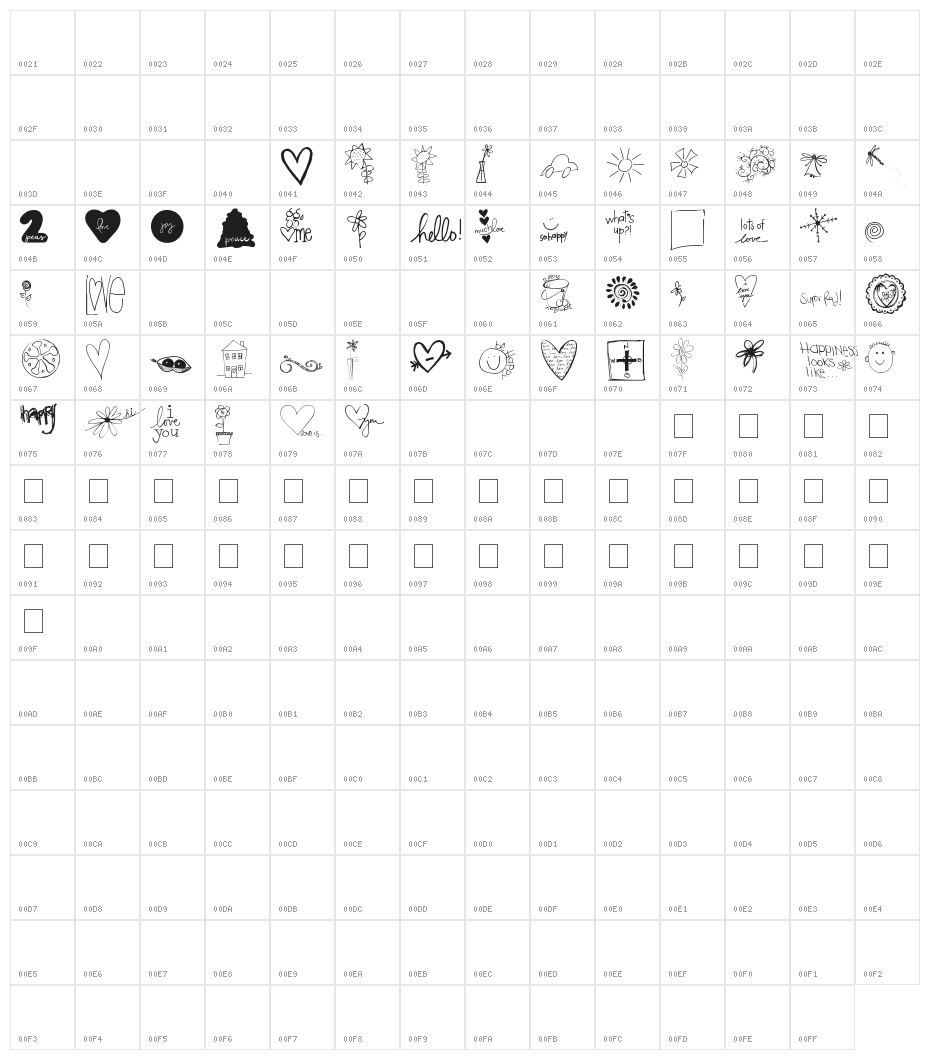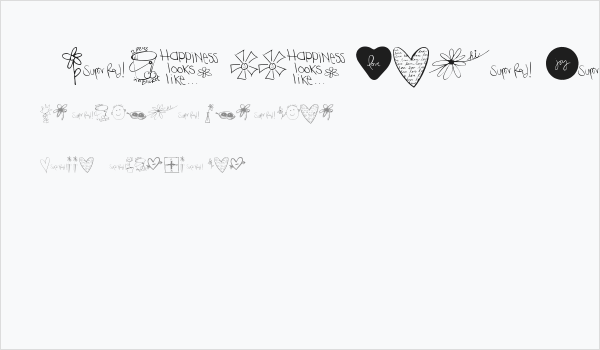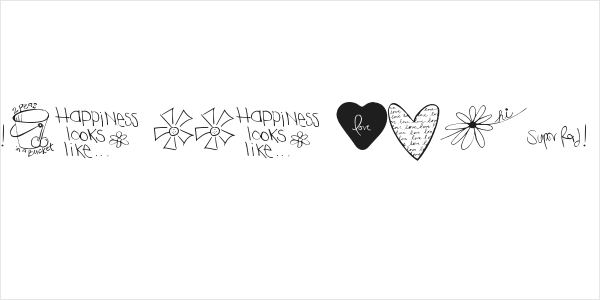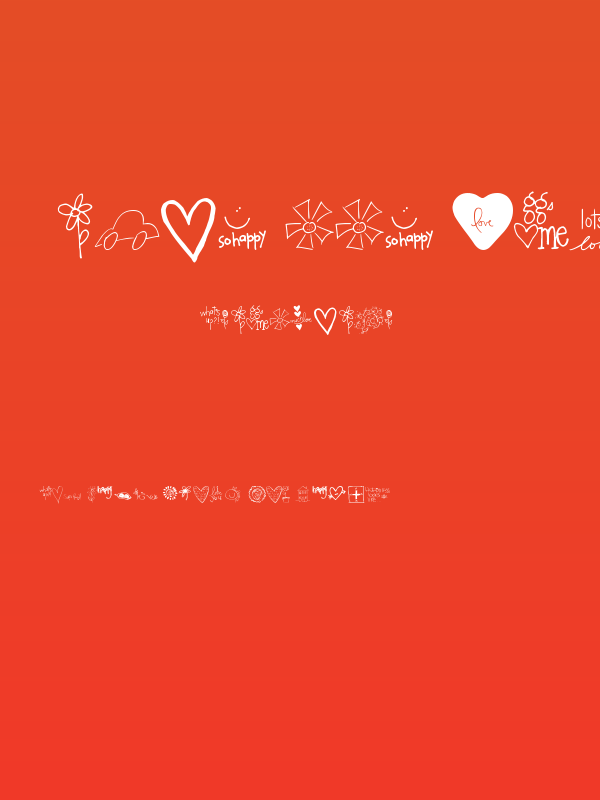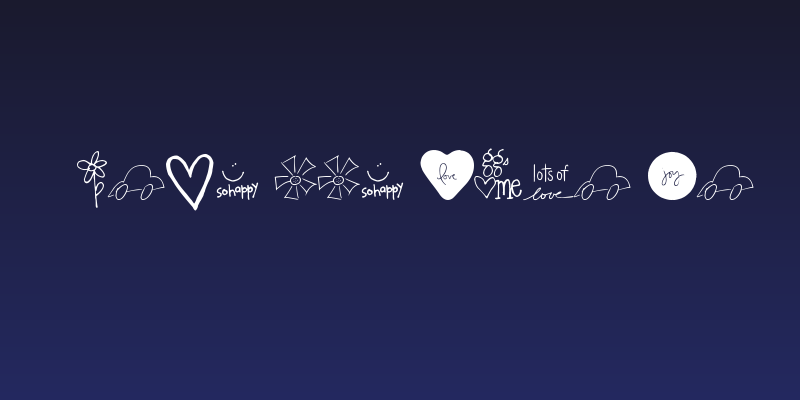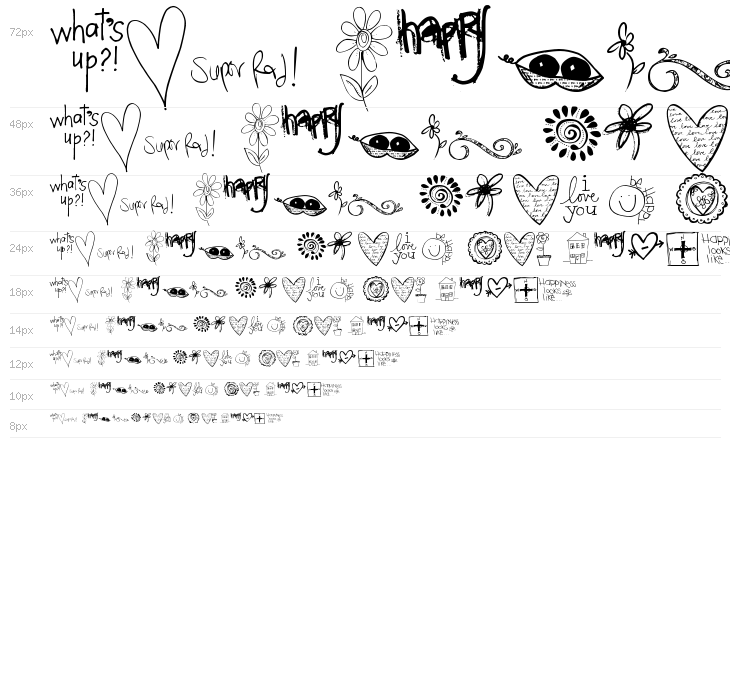
2Peas GGs Love Me Font
| 名称 | 2Peas GGs Love Me |
| 分类 | Valentine |
| 整体风格 | Whimsical, Playful, Artistic |
| 使用场景 | Decorative elements, Creative projects |
| 推荐项目 | Ideal for greeting cards, scrapbooking, personal stationery, and creative projects that require a fun and informal touch. |